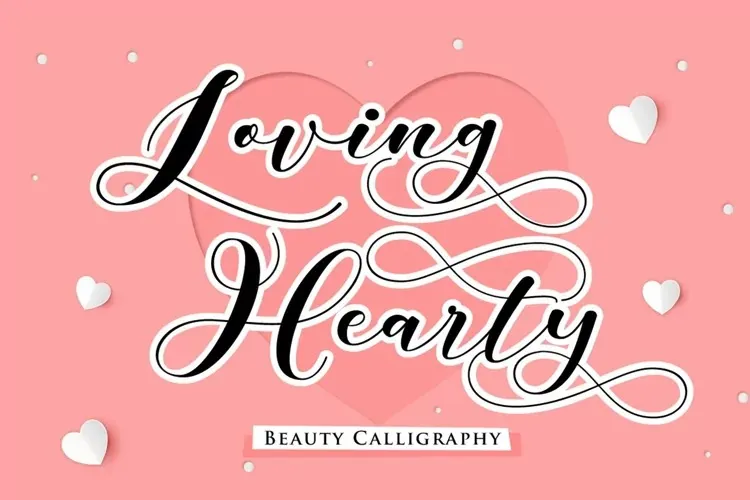
A fonte Loving Hearty é perfeita para aqueles que desejam um ar sofisticado e elegante em sua marca ou projeto. Com seu design delicado e encantador, esta fonte script está projetada especialmente para estilos de negócios como moda, comércio eletrônico, blogs de tendências e boutiques de casamento que desejam se destacar. Com uma riqueza única em sua tipografia, a Loving Hearty oferece um toque romântico e elegante ideal para criar mensagens impactantes. Seja você um designer gráfico ou criador de conteúdo digital, essa fonte é certamente o item que está procurando para dar um toque definitivo aos seus trabalhos. Ela será uma ótima opção para quem busca manter a personalidade única em sua marca enquanto se destaca no mercado, proporcionando ao seu trabalho um ar sofisticado e encantador.